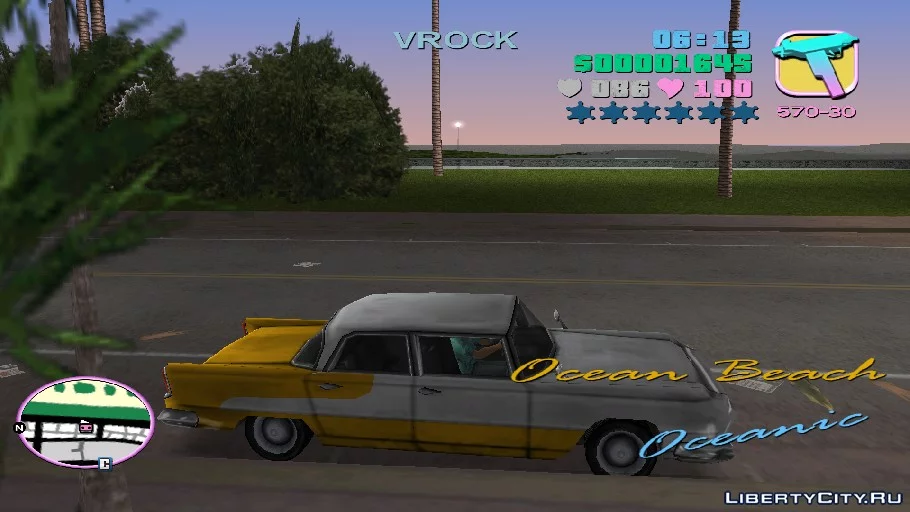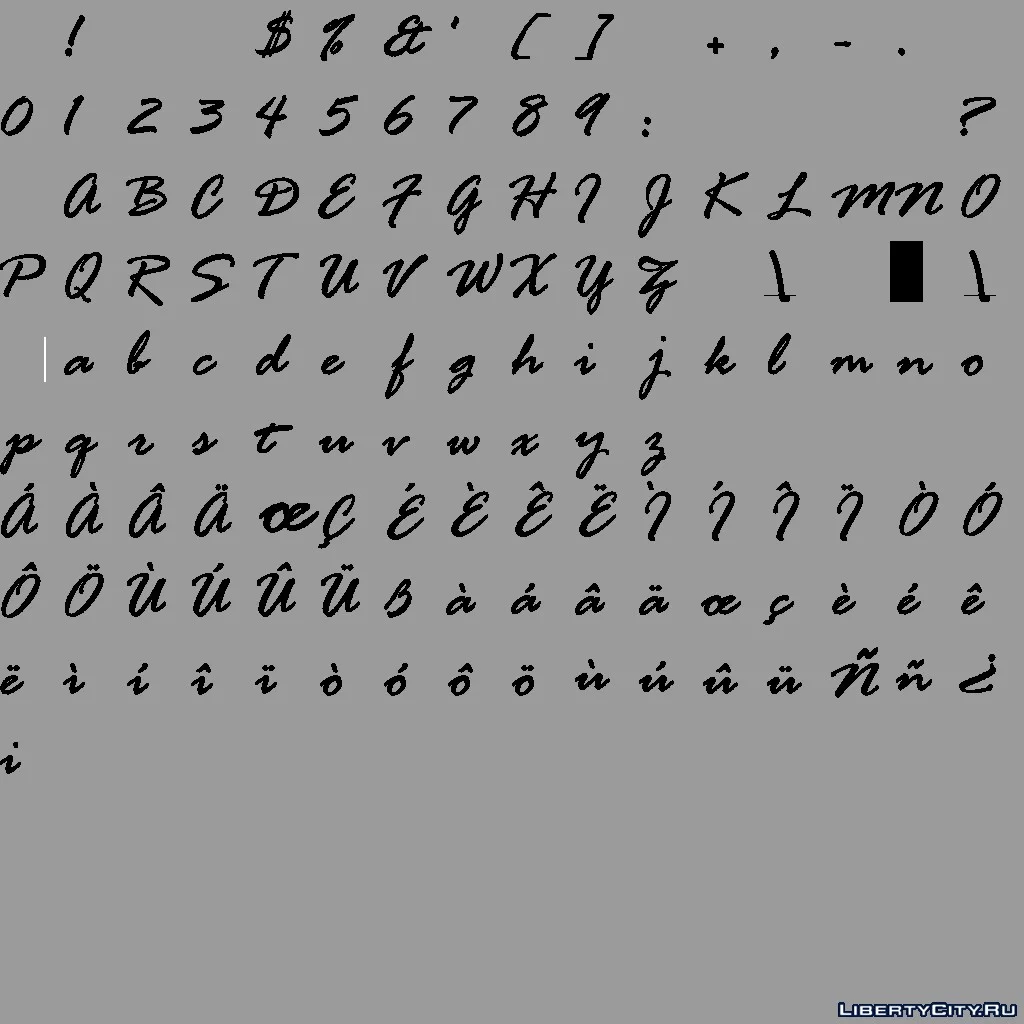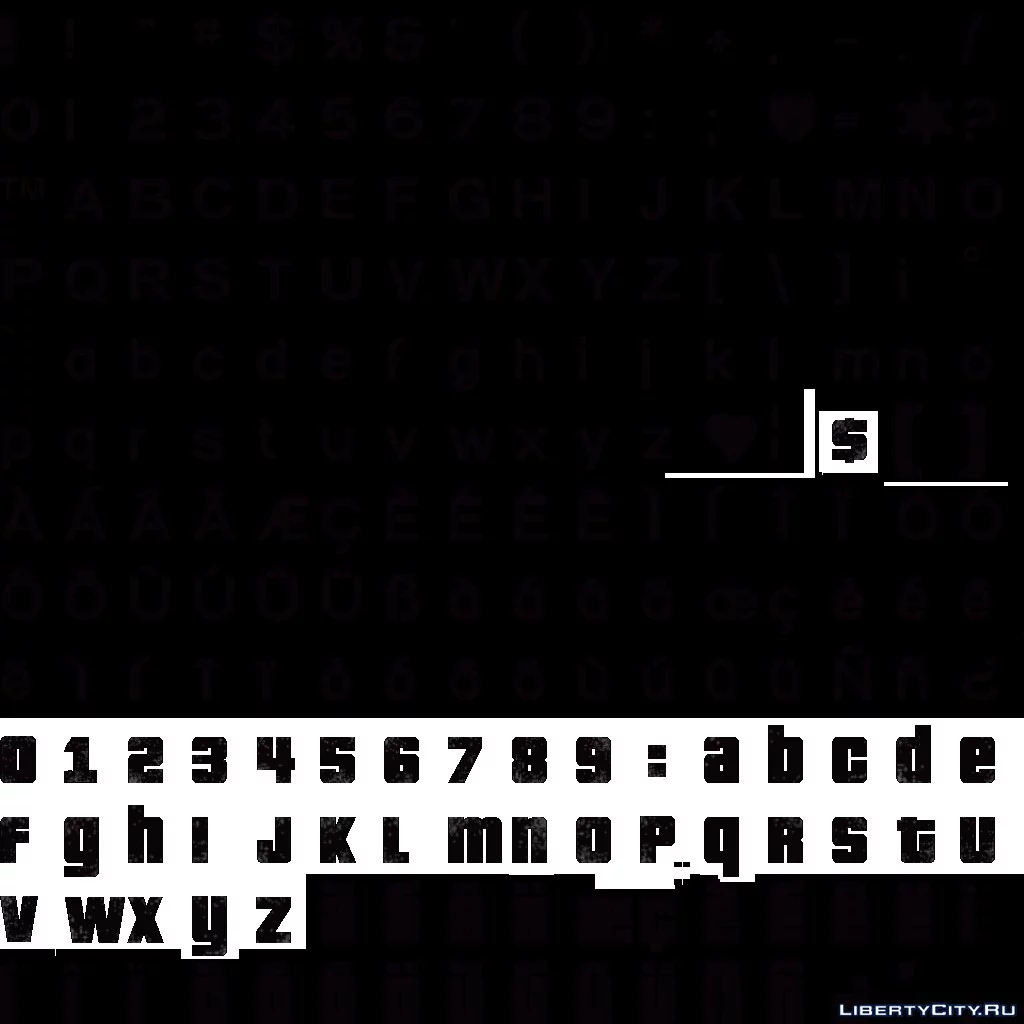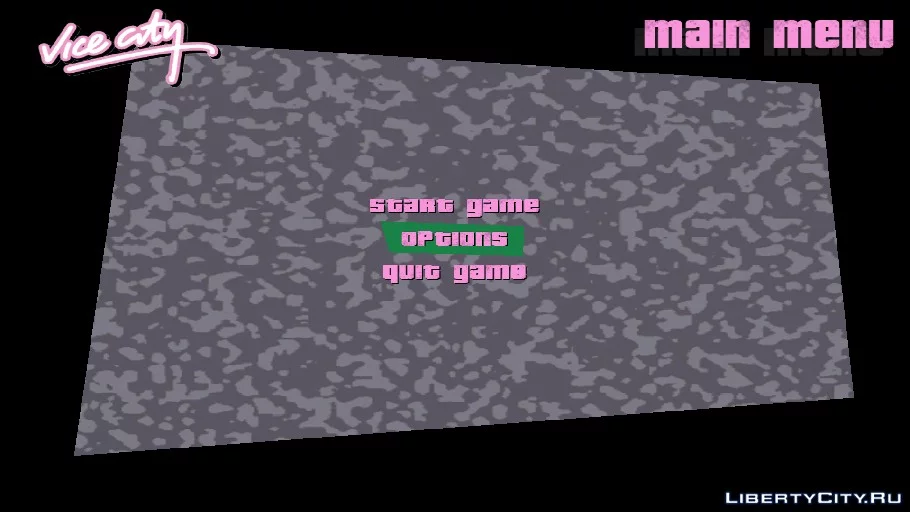
Оригинальные шрифты в HQ
Стандартные шрифты в HQ. Сохранены детали. Скриншоты большего размера в архиве. Тонкий шрифт на подобии Arial (самый простой) не включает в себя символы с дополнительными знаками (Ё и др.) в HQ, в остальных они есть.